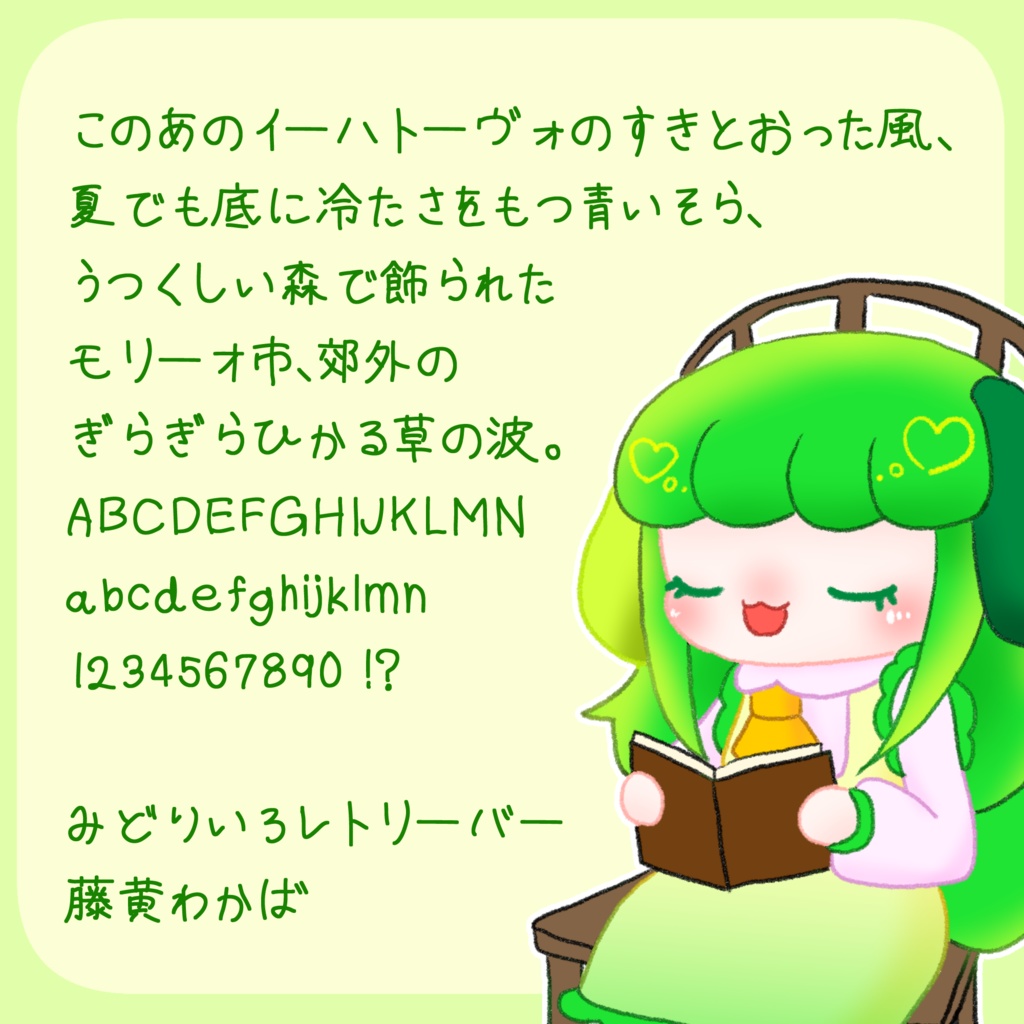
わんちわ手書きフォント
藤黄わかばの手書き文字がフォントになったよ! 普段さらっと書く感じで書いてみたよ! 使ってみて「この文字を追加してほしい!」というのがあったら ショップメッセージかTwitterDM(@touou_wakaba)へ連絡ください! 可能そうなら随時対応文字増やしていきたいなと思ってます! フォントの様子は動画からも確認できます!合わせてご確認ください! 使用ツール:iFontMaker 形式:True Type ☆収録文字☆ ・アルファベット(大文字・小文字) ・数字 ・ひらがな ・カタカナ ・漢字(2137字) ・記号 【ご利用について】 ・個人利用(スマホやPCへの設定など個人で楽しむ分)についてはご自由にどうぞ! ・WEBデザイン、印刷物、映像、グッズ等に使用する際はTwitterDMへ使用用途と合わせてご連絡ください。 個別での許可制とさせていただきますが、問題なければ商用目的の場合でもOKにしたいと考えています。 なお、「藤黄わかば」の切り抜き動画に関しては事前報告なしで作成可能ですが、そのかわりに完成した動画は見せてほしいです…! 連絡先 https://x.com/touou_wakaba 【禁止事項】 ・使用連絡なし、もしくは却下された場合で商用利用すること。 ・公序良俗に反する目的、誹謗・中傷目的での利用。 ・販売データを再配布・自作発言すること。